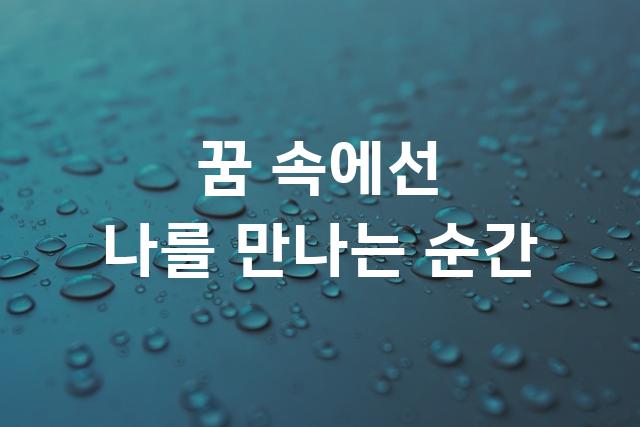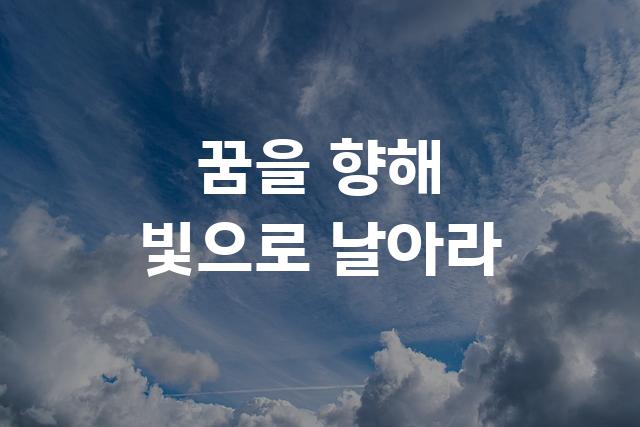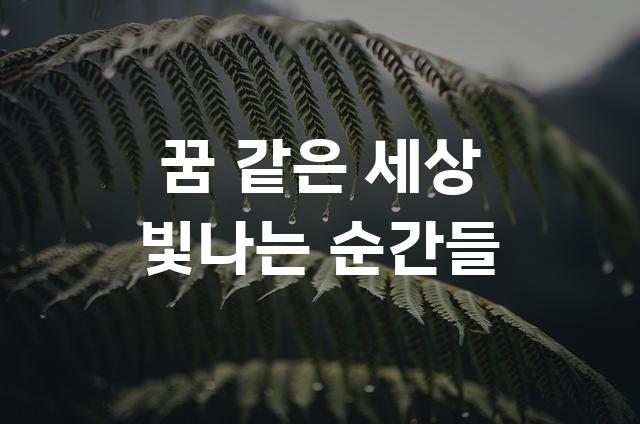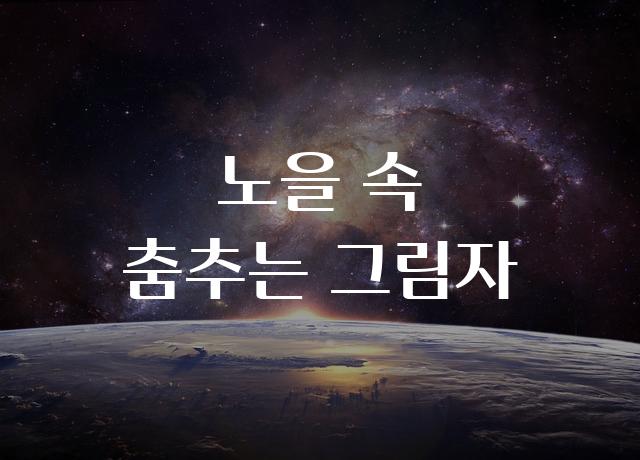
레페리포인트 Special은 현대적인 미학과 전통적인 고딕 스타일을 결합한 폰트입니다. 제목용으로 디자인된 이 폰트는 강렬하고 장식적인 요소가 특징입니다.
레페리포인트 Special은(는)
기본 고딕, 장식 스타일, 감성적인, 부드러움, 별모양/패턴, 길고/크고 계열의 생김새를 가지고 있으며
로고 디자인, 브랜딩, 제품 포장 등에서 자주 활용되며, 효과적인 메시지 전달에 적합합니다.
이 폰트는 광고/마케팅, 패션/뷰티, 소매/유통 분야에 잘 어울리며,
세련된, 전문적인, 고급스러운 느낌을 담고 있는 것이 특징입니다.